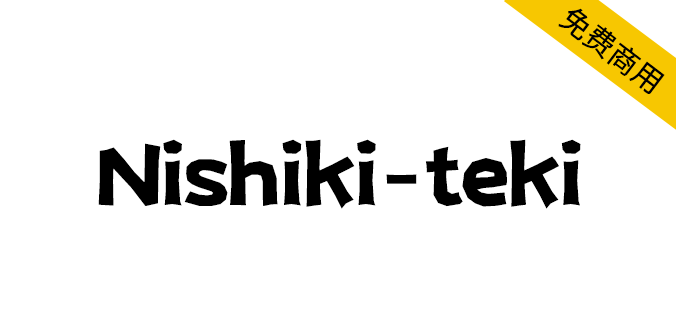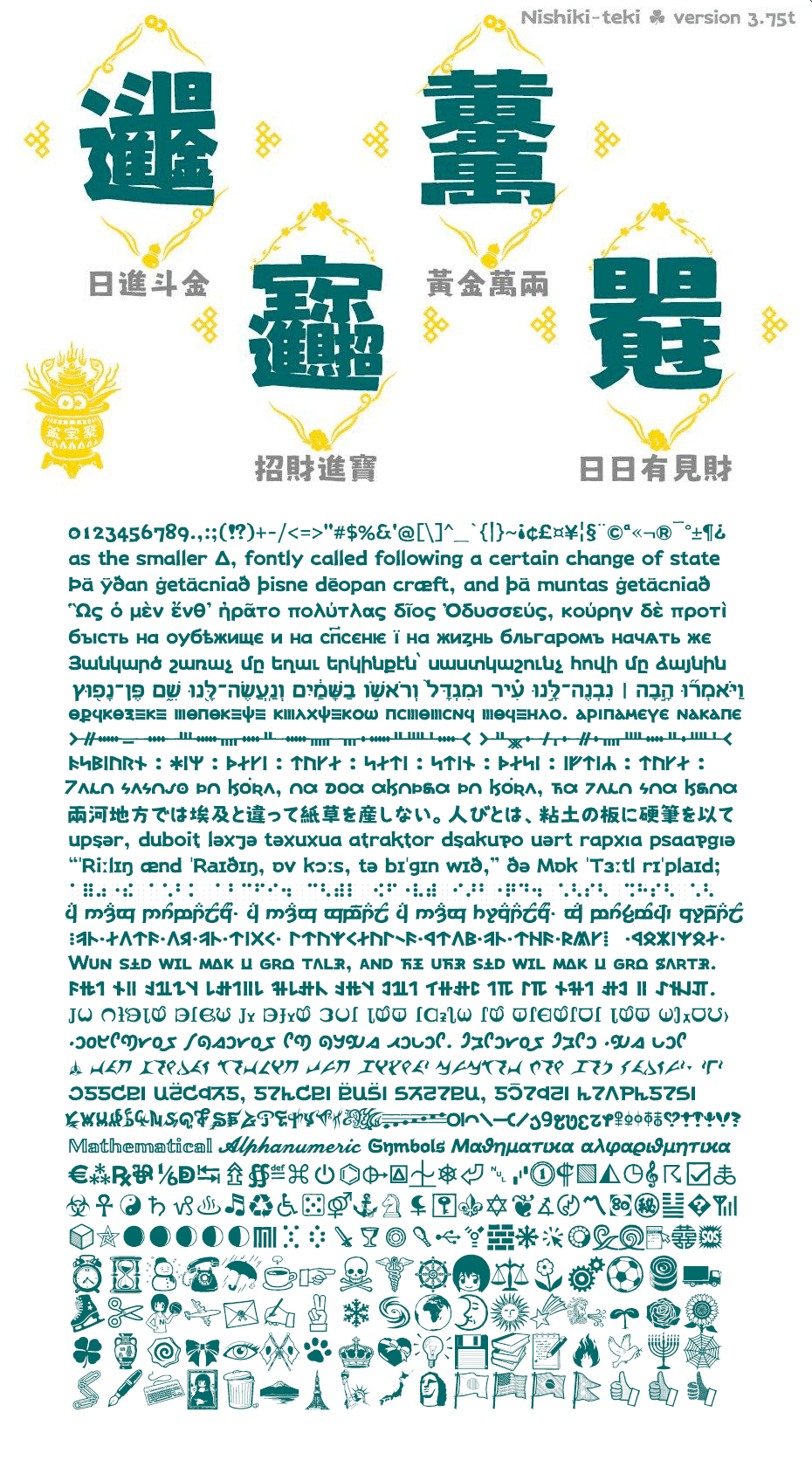
Nishiki-teki是一款可爱的马克笔手绘风格日系免费商用字体。当前版本包括:拉丁语、希腊语、西里尔语、亚美尼亚语、希伯来语、格鲁吉亚语、奥格姆语、北欧古语、科普特语、格拉哥里语,平假名,片假名,注音,汉字,傈僳语,大阪,音标,盲文图案、一定量的表情符号、各种符号和标点符号等。
注意:Nishiki-teki字体不适合用于简体字,因为缺字严重,适用于繁体和日语,如果需要简体版,请选择“猫啃什锦黑”,猫啃什锦黑是专门针对Nishiki-teki字体进行简体字补充的一款字体。